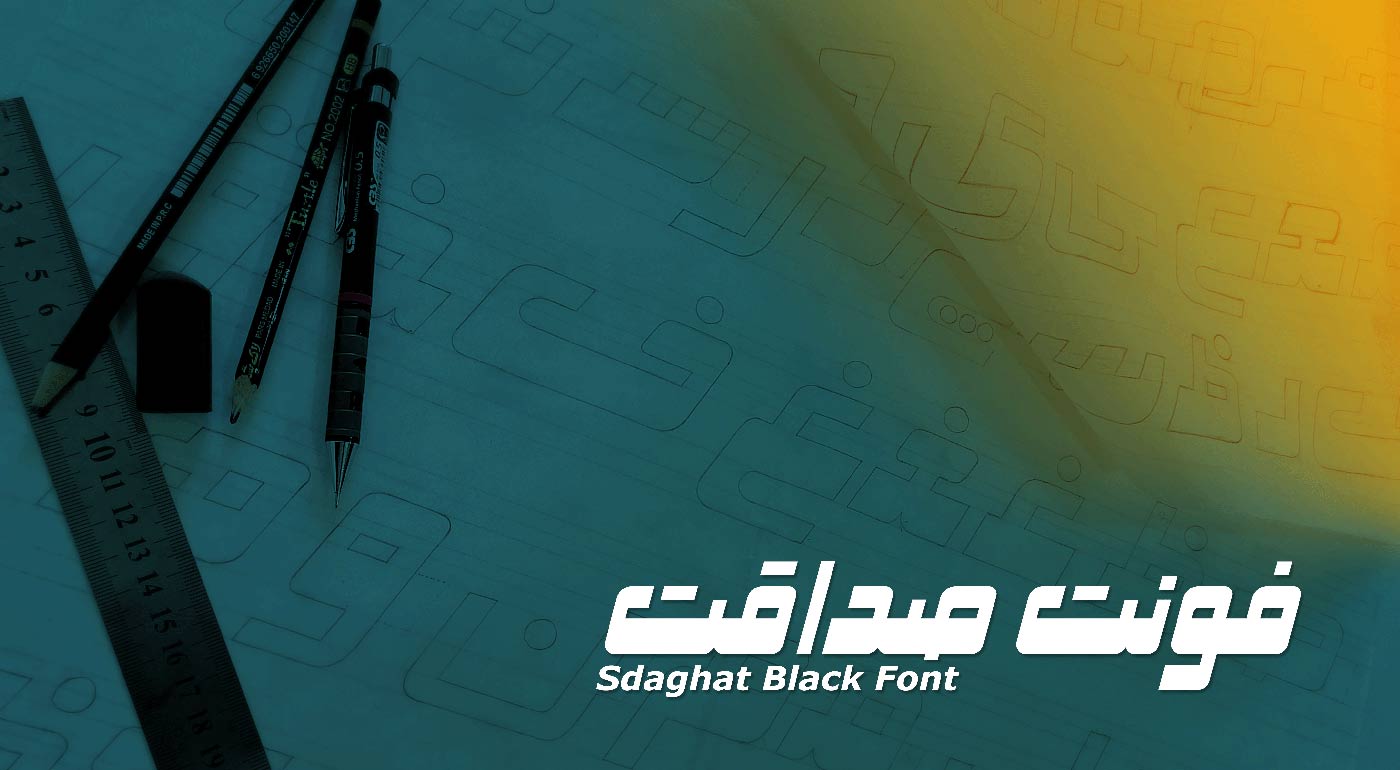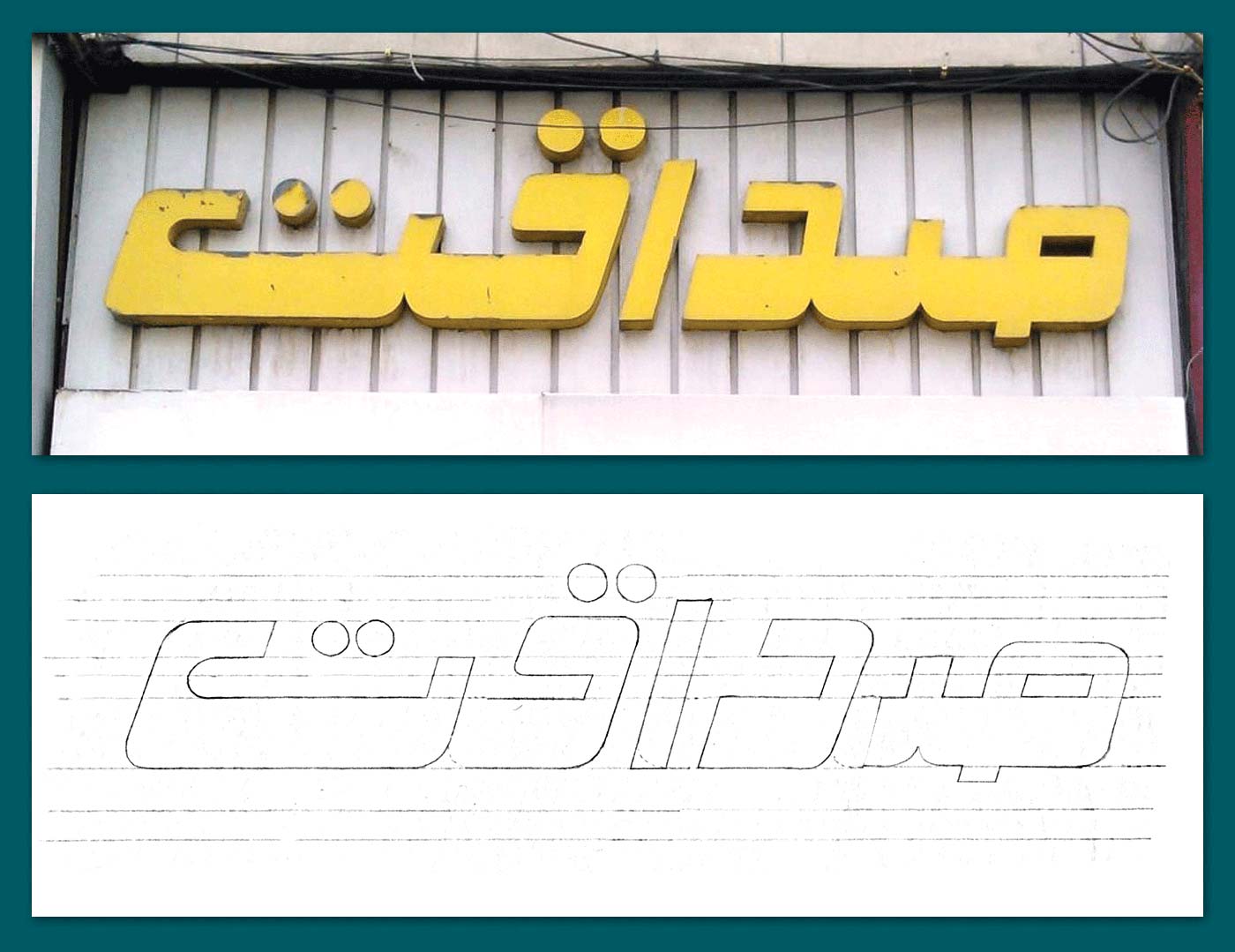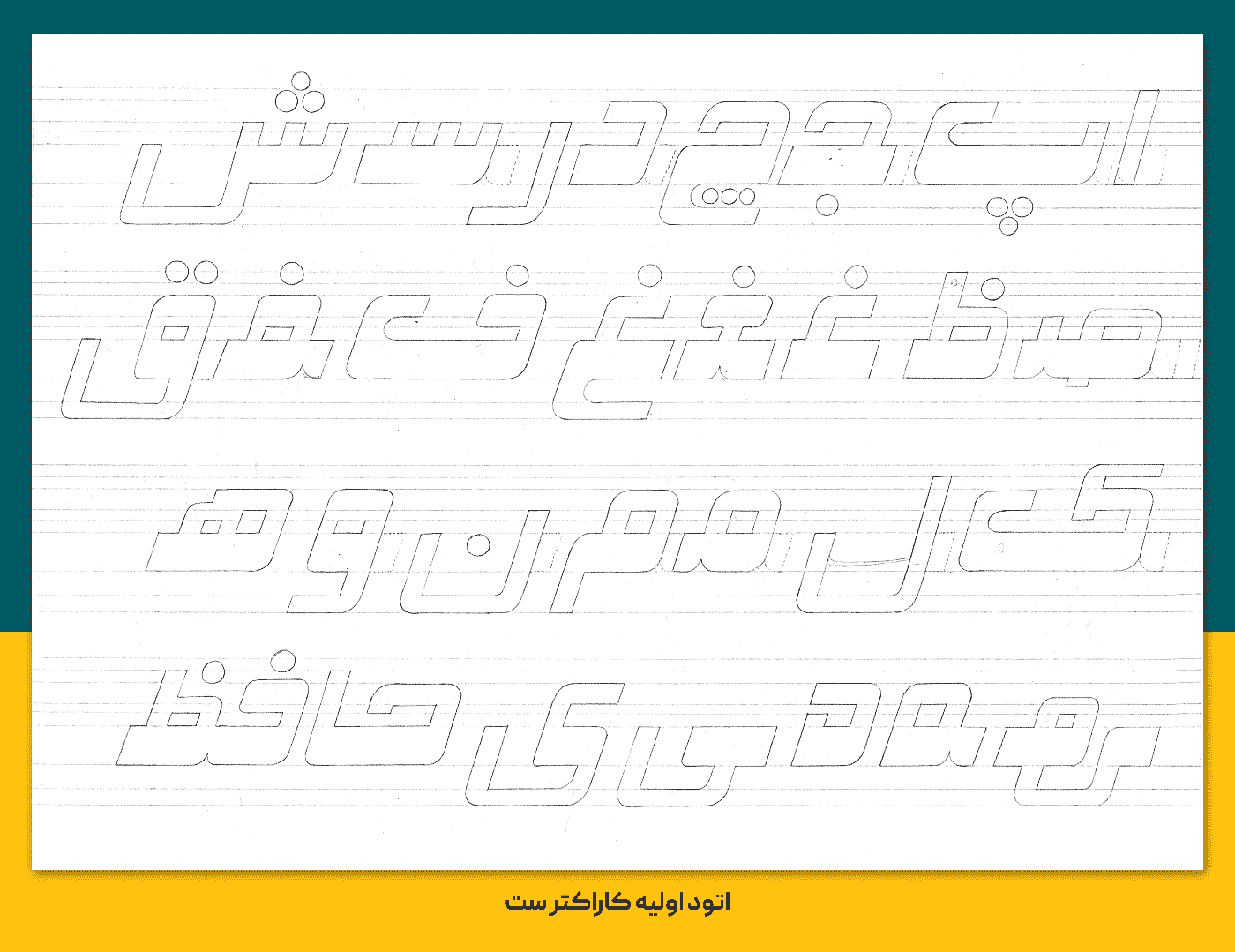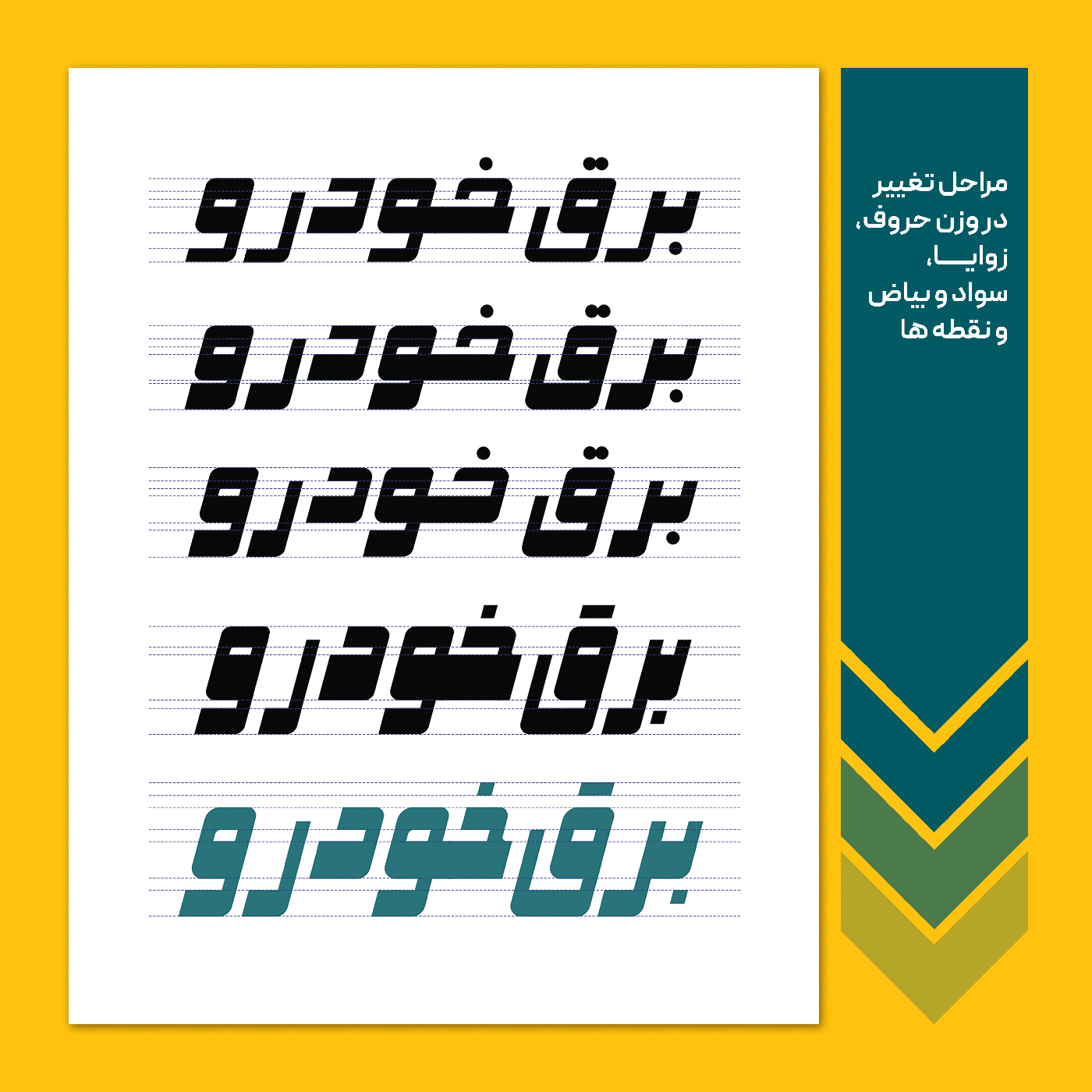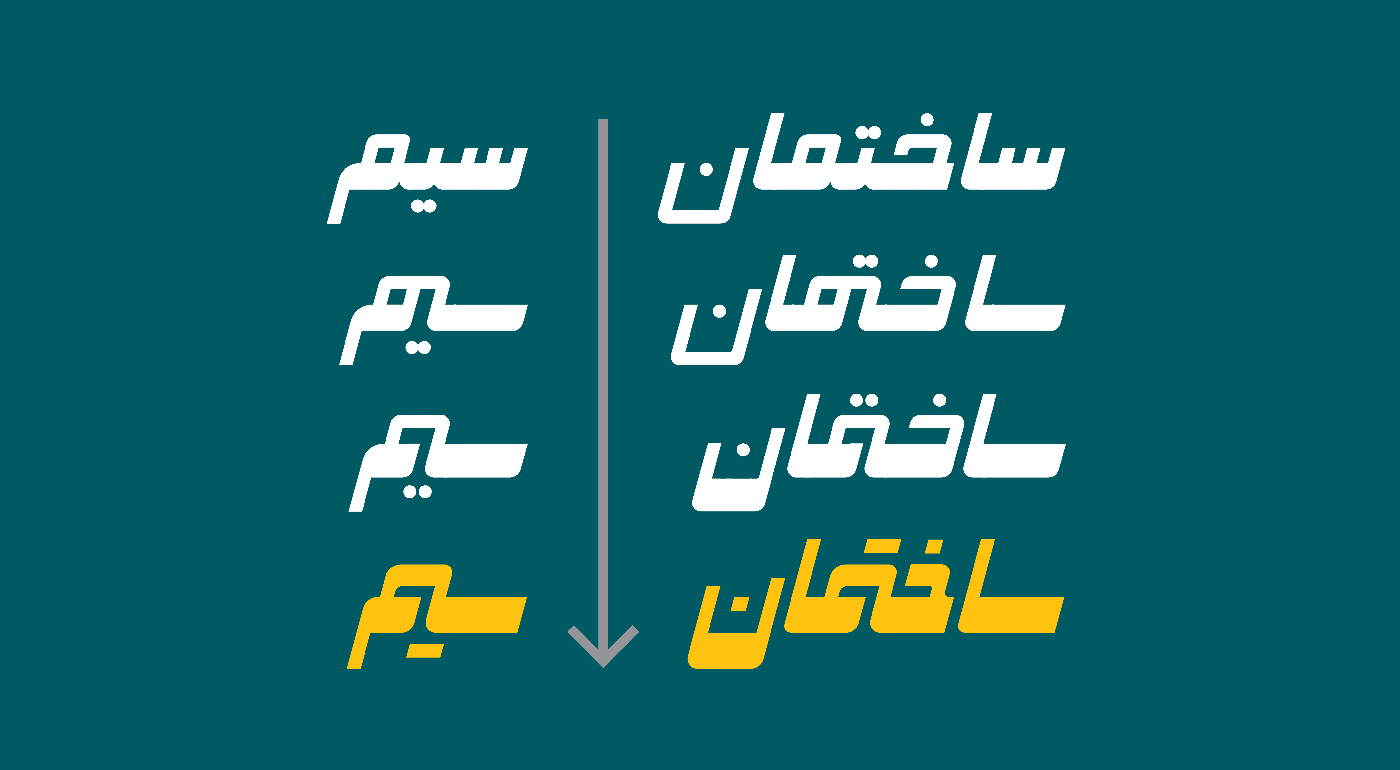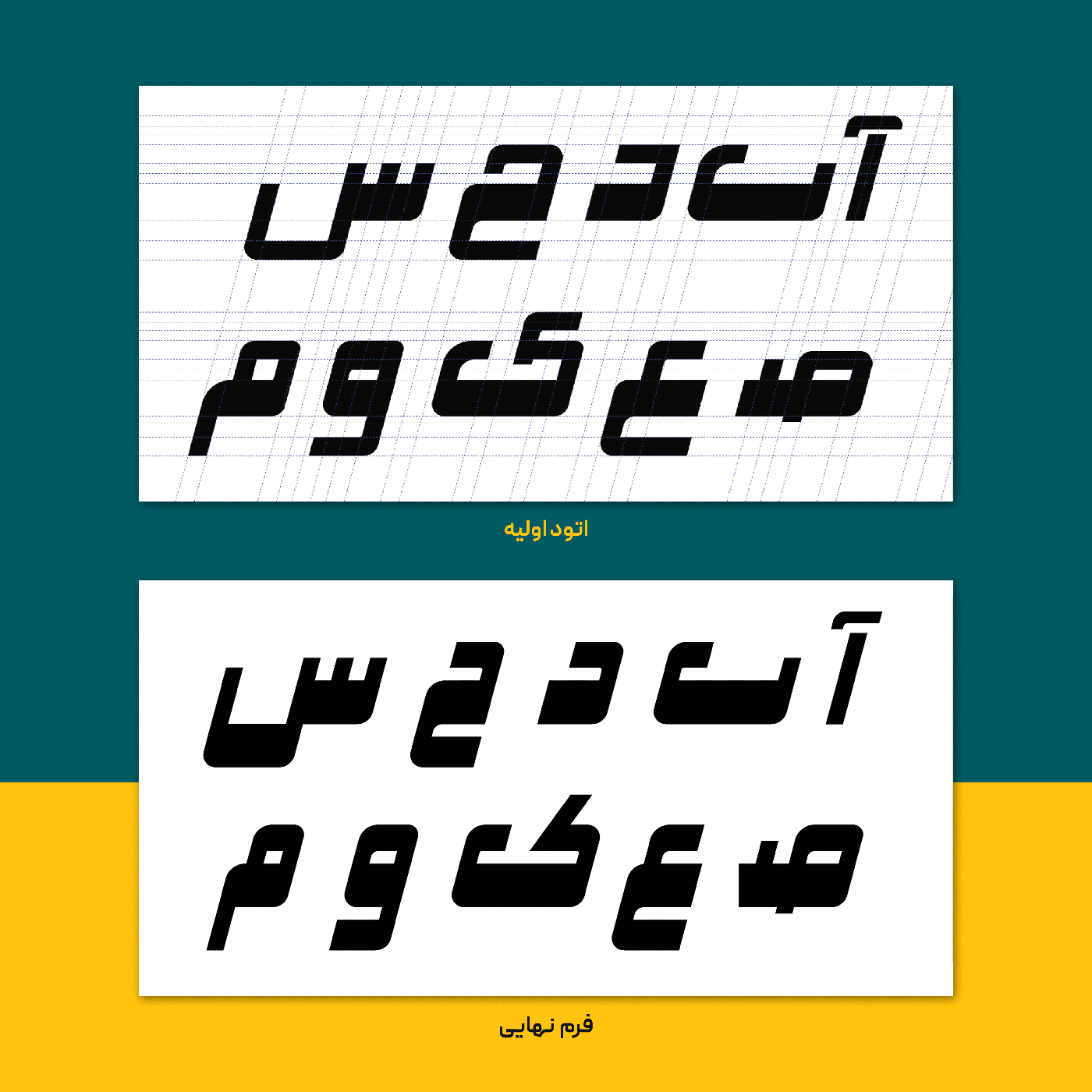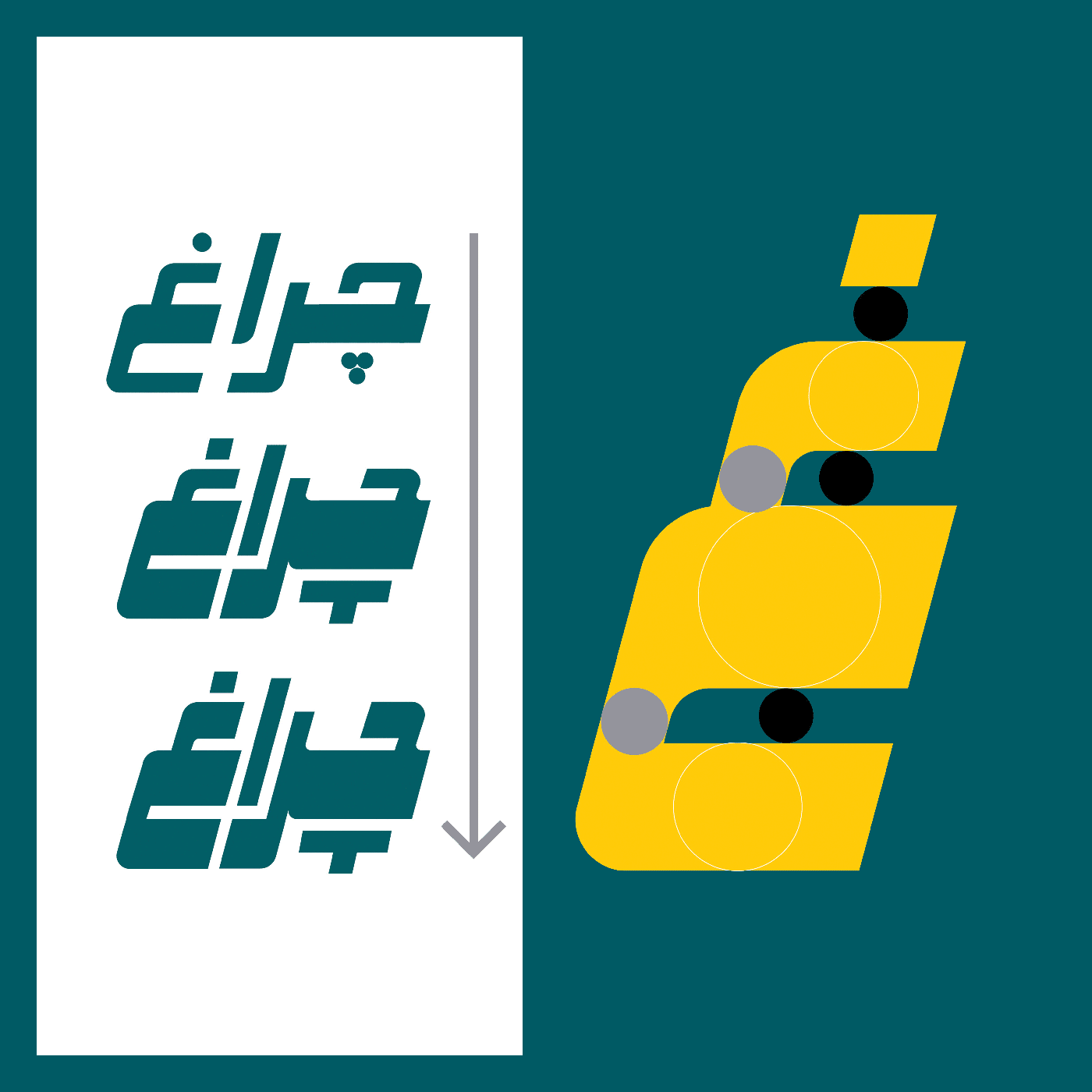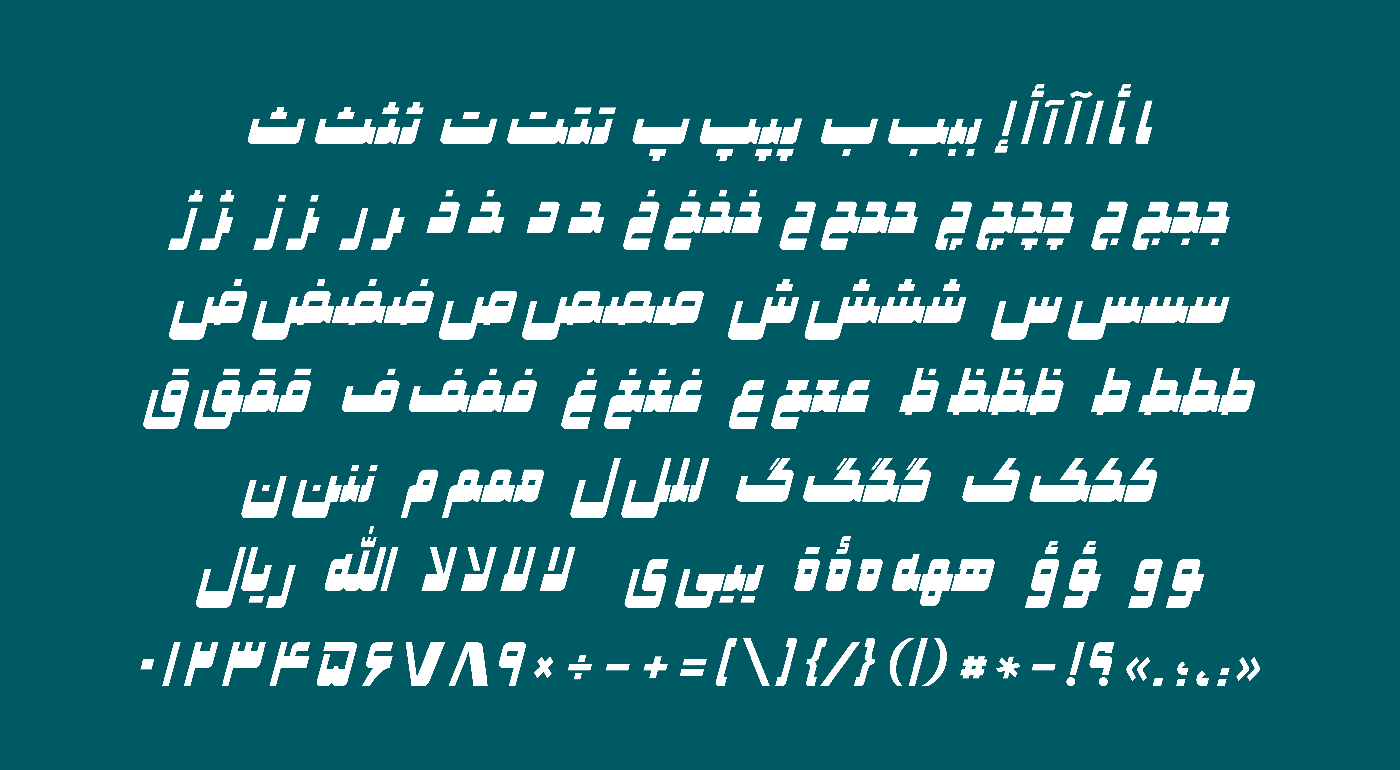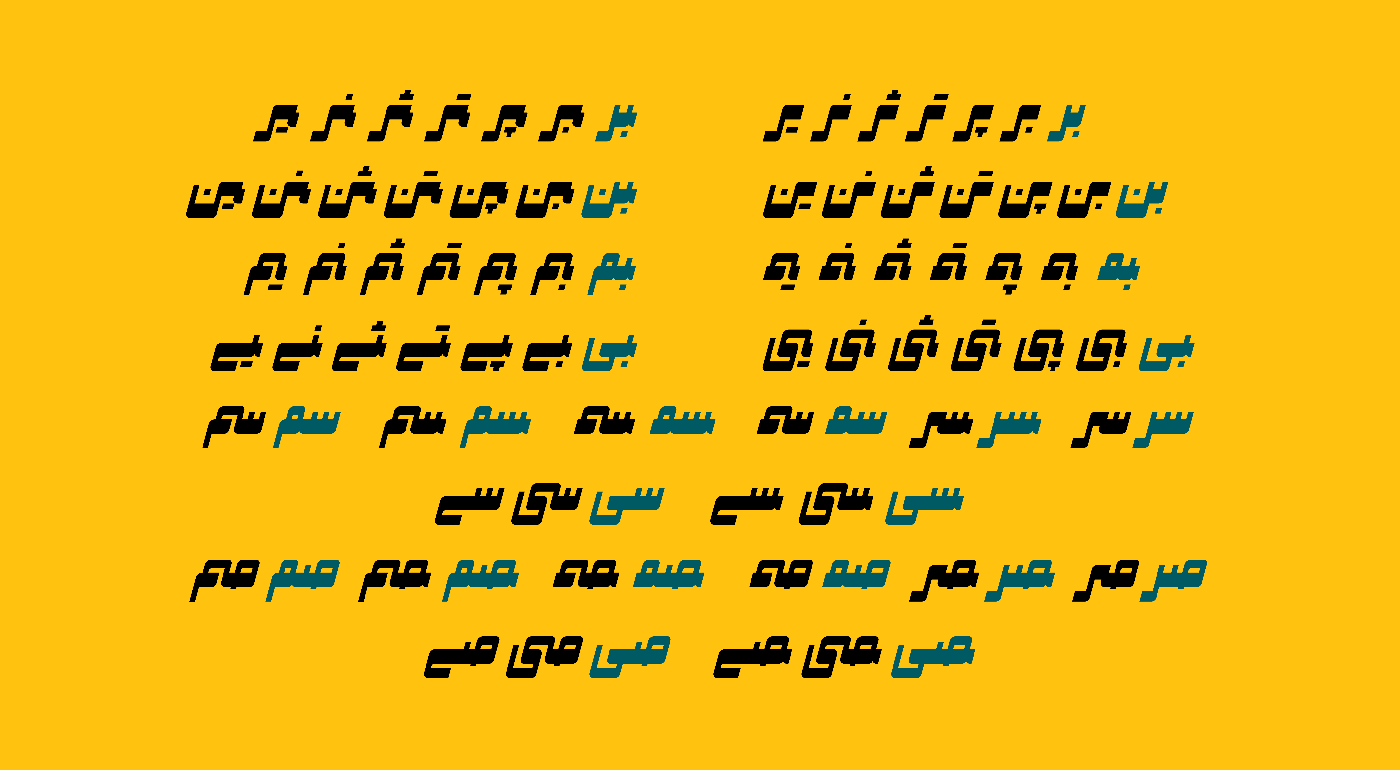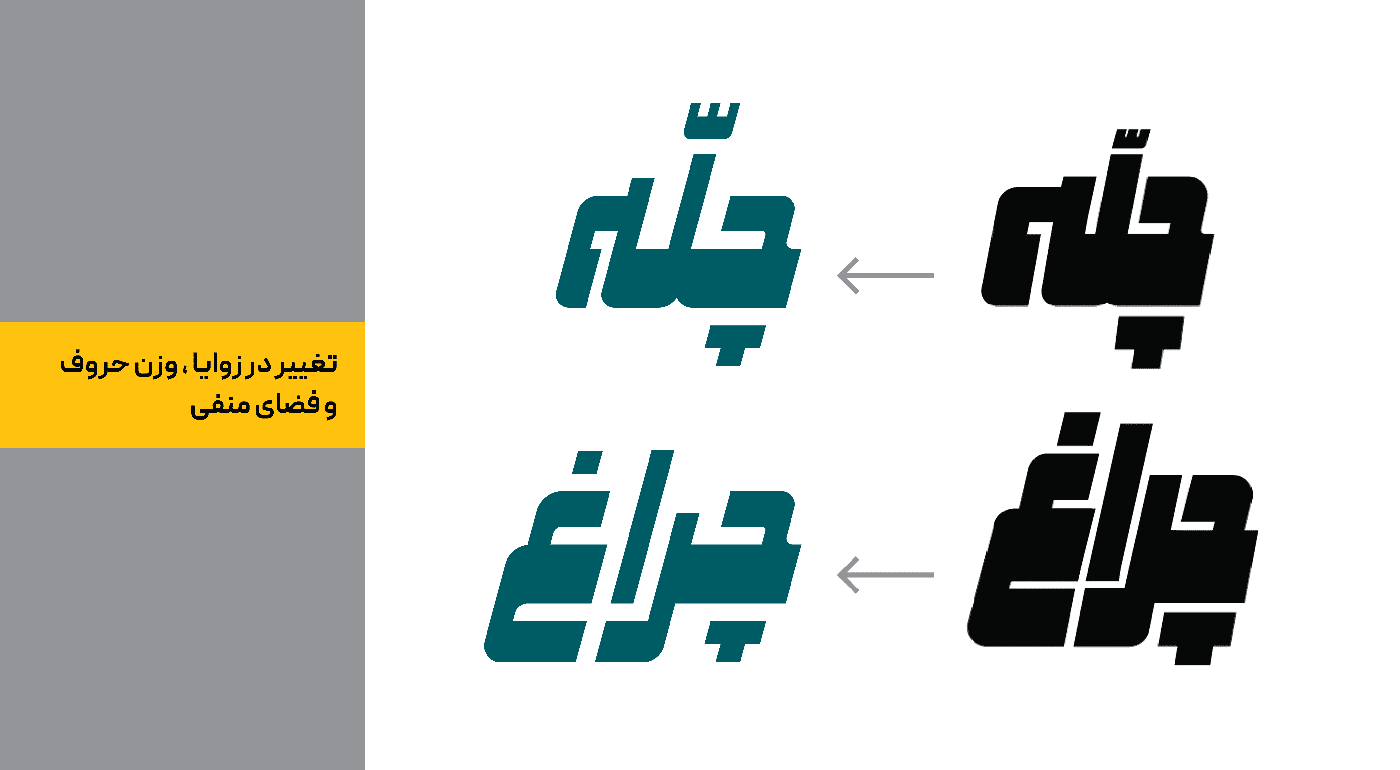
این فونت فقط حاوی حروف فارسی و عربی است.
ایده اولیه فونت صداقت از یک تابلوی قدیمی حروف برجسته به همین نام گرفته شد و پس از بررسی فرم حروف موجود و طراحی بقیه حروف بر مبنای بیس اصلی، اتودهای اولیه آماده شد ؛ سپس با چندین مرحله تغییرات در فرم حروف ، زوایا ، ضخامت ها ، سواد و بیاض ها و نقطه ها تایپ فیسی مدرن با حال و هوای تایپوگرافی های قدیمی طراحی شد . این فونت قابل استفاده در فضای پوستر ، طراحی لوگو، طراحی عنوان و تیتر ، تابلوسازی و … میباشد.
در تصویرهای زیر مراحل طراحی و شکل گیری فونت صداقت را میبینید.
طراح در چند مرحله وزن حروف، زاویه ها ، نسبت سفیدی و سیاهی و نقطهها تغییر داده است تا به بهترین نتیجه دست یابد.
حروف جایگزین در فونت صداقت
در فونت صداقت برای رسیدن به حالت های مختلف حروف مانند ح و ع لبه دار و ک / ب / ف کشیده یا لبه دار و همچنین استفاده از ترکیب های جدید مانند اتصال دندانه افراشته ص / س / ب / ن / ی به حروف ر / ن / م / ی باید از ترکیب شیفت و همزه برای انتهای کلمه یا حروف جدا و از همزه برای بین حروف استفاده کنید.
فونت صداقت مناسب تایپوگرافی و طراحی لوگوتایپ است.